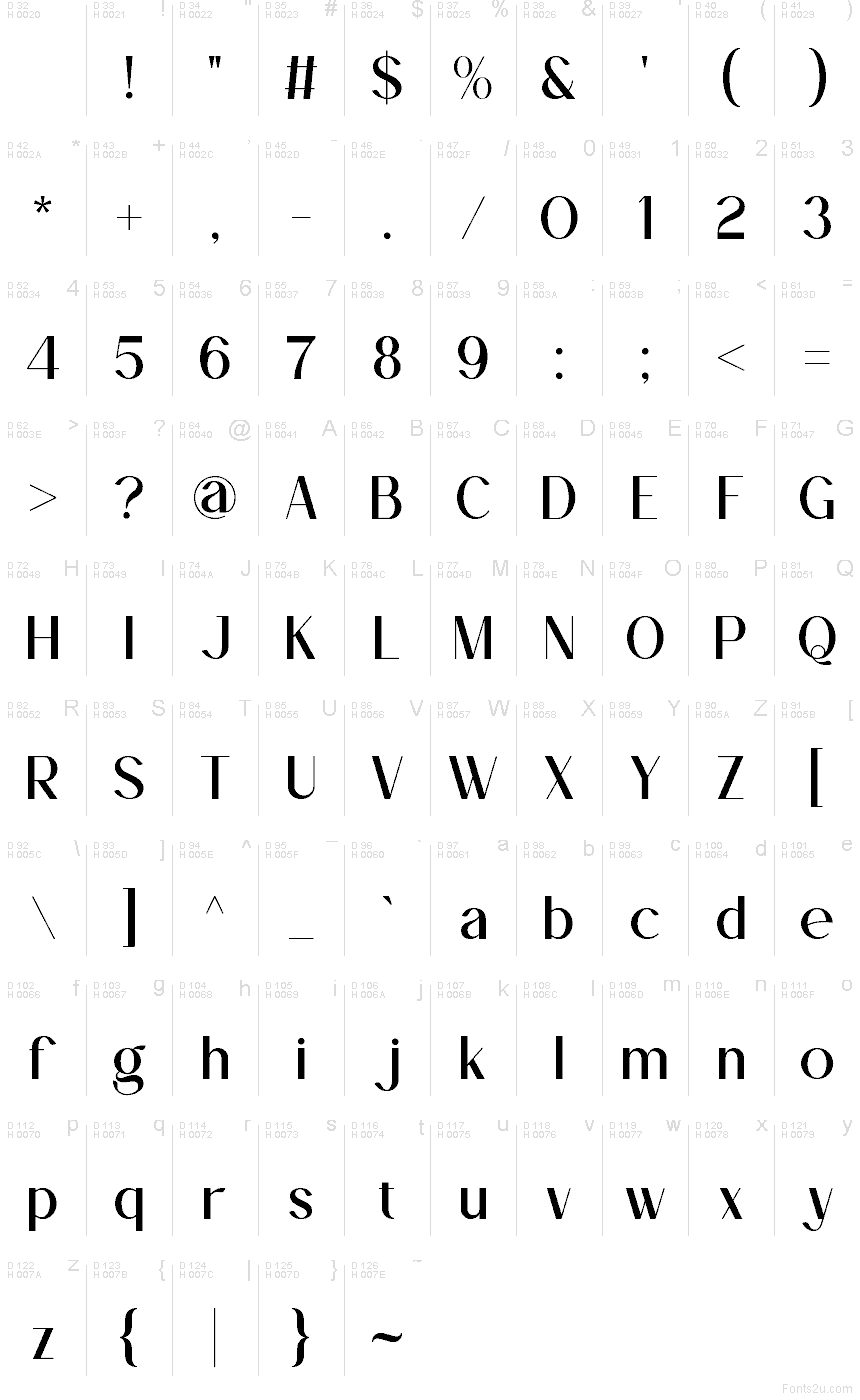
Megiko, da Ermedia Studio, é uma fonte sem serifa gratuita com proporções imponentes e uma transição extraordinariamente nítida entre traços verticais largos e barras ultrafinas. Suas curvas abertas e junções estreitas lembram os cabeçalhos de revistas de moda.
As embalagens são um cenário especialmente adequado para esse letreiramento, pois sua escala elegante e seus contrastes definidos combinam com rótulos de perfumes e campanhas de cosméticos com foco no luxo. Em capas editoriais e cartazes de eventos culturais, sua silhueta alongada pode se tornar o cerne de uma identidade de marca refinada em uma linha coordenada de produtos ou campanha sazonal, em vez de servir apenas como uma tipografia neutra.